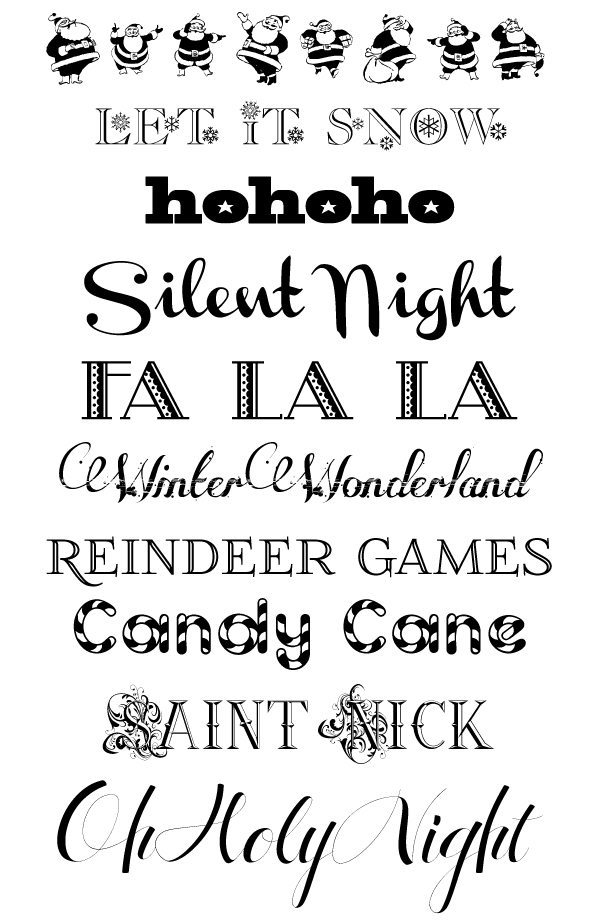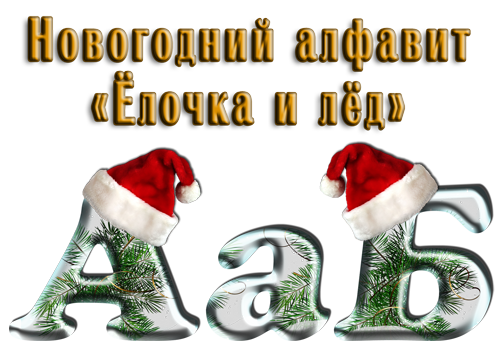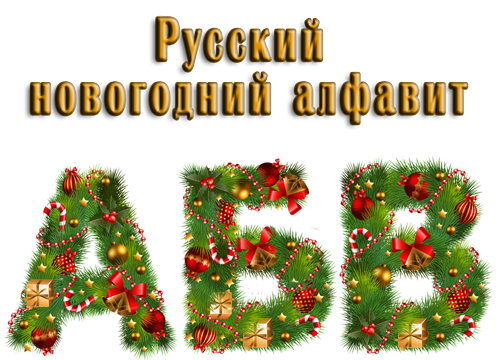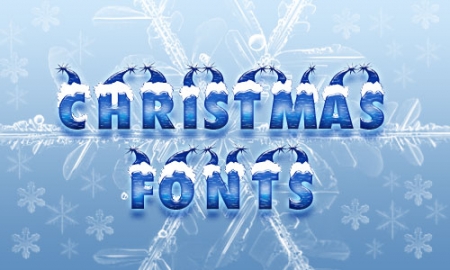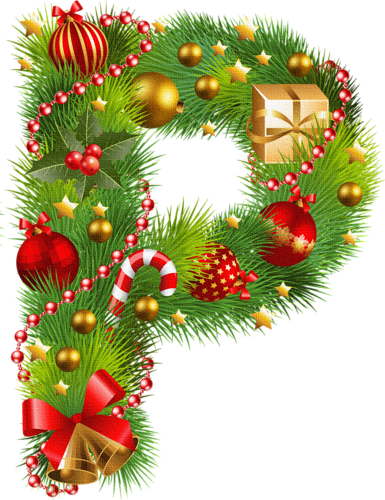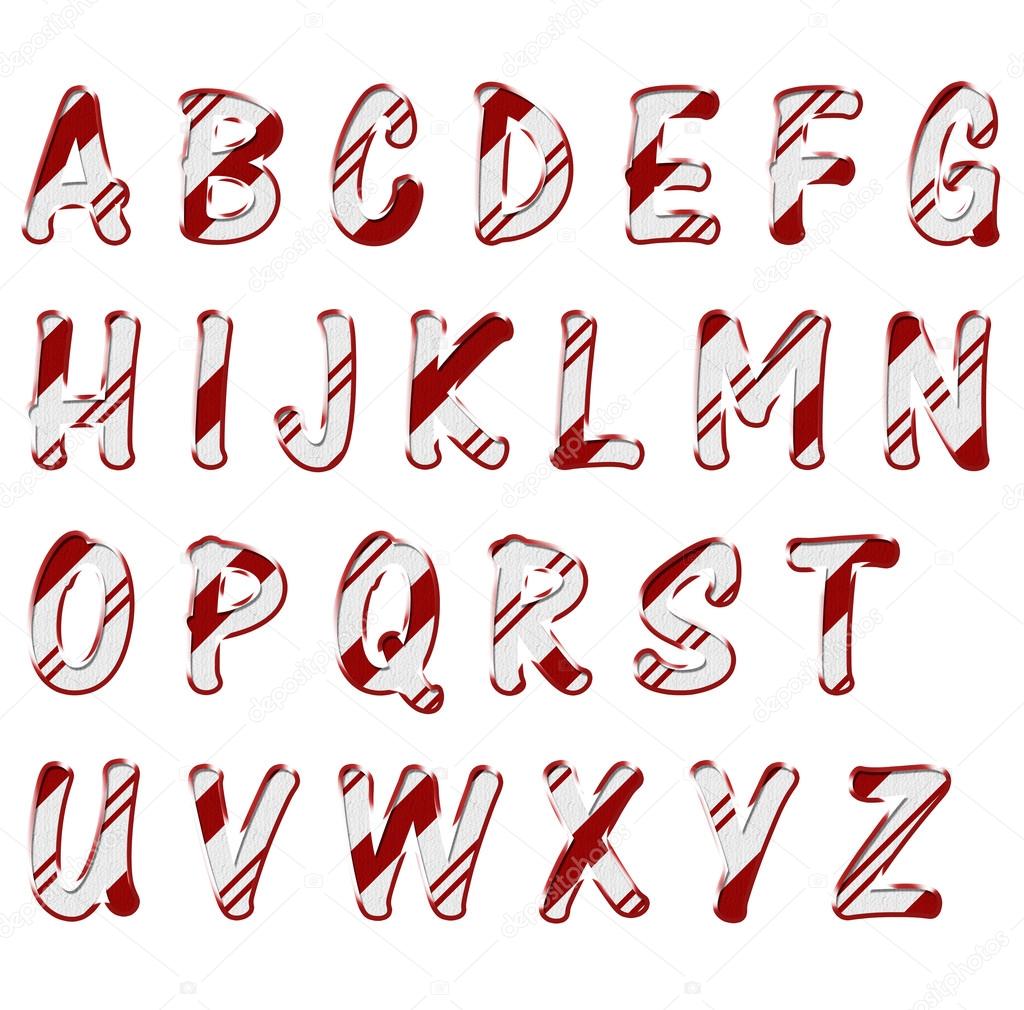
Вязаный шрифт кириллица. Лучшие бесплатные шрифты для дизайнеров
Шфриты в веб-дизайне вещь практически незаменимая. Используя при разработке дизайна сайта нестандартные и оригинальные шрифты вы можете достичь поистине удивительного результата. Разработка баннеров, иллюстраций, разного рода афиш и других нестандартных текстово-графических материалов без специальных шрифтов и вовсе невозможна. В данном разделе блога вы найдете разные англоязычные и русские кириллические шрифты для фотошопа и сможете понравившиеся вам экземпляры шрифтов скачать бесплатно.
Все материалы разделены и скомпонованы в отдельные наборы по тем или иным тематикам — каллиграфические, готические, новогодние, оригинальные, рукописные и многие другие шрифты к вашим услугам.
В мега-наборе всяческих материалов для хэллоуина иконок, фонов, вектора и т.п. мы публиковали в том числе и страшные шрифты для Фотошопа. Однако тогда это было лишь частью большой статьи, и должного внимания им уделить не получилось. Сегодня исправим эту ситуацию, т.к. в нашем распоряжении будет полноценная заметка. По факту эта ниша больше всего схожа размытыми нечеткими и декоративными шрифтами и может содержать некоторые нестандартные элементы в буквах….
Название сегодняшних материалов в подборке полностью определяется способом их создания — это шрифты печатной машинкой. Теоретически, по форме и стилистике они должны соответствовать реально напечатанным текстам. Похожий принцип типографики встречался в заметках про граффити или надписи мелом на доске — по данным наименованиям вы сразу четко представляете их внешний вид.
Google Fonts — один из самых крупных архивов реально бесплатных шрифтов с сотнями гарнитур. Учитывая его универсальный характер и всеобщую доступность, теряется практически любой смысл использования обычных шрифтов по умолчанию. С помощью сервиса вы сможете реализовать разные нестандартные примеры типографики. В данной статье найдете подборку из 10-ти бесплатных шрифтов Google Fonts, которые идеально подойдут для оформления заголовков сайта. Они установлены во многих веб-проектах по всему миру. Материал…
В данном блоге вы уже могли встречать специальный раздел для поиска и скачивания русских кириллических шрифтов. Статьи там отсортированы по различным тематикам дабы дизайнерам было проще подбирать нужные им файлы. Это удобно, когда требуется подобрать, например, жирный, рукописный или декоративный вариант. Сегодня мы хотим представить вам подборку лучших архивов русских шрифтов онлайн аналогичных проектам Urbanfonts, Dafont и др.
В данной статье сможете бесплатно скачать шрифты мела для фотошопа, которые пригодятся вам в разных дизайнерских решениях на сайтах, иллюстрациях, приложениях или даже в офлайне (например, иногда владельцы кафе оформляют меню в этом стиле). Подобный вариант с декоративным шрифтом надписи мелом также неплохо будет смотреться в полиграфии. Где бы вы его не применили, подборка ниже окажется полезной. Всего собрали около 50-ти объектов на любой вкус. Перед тем,…